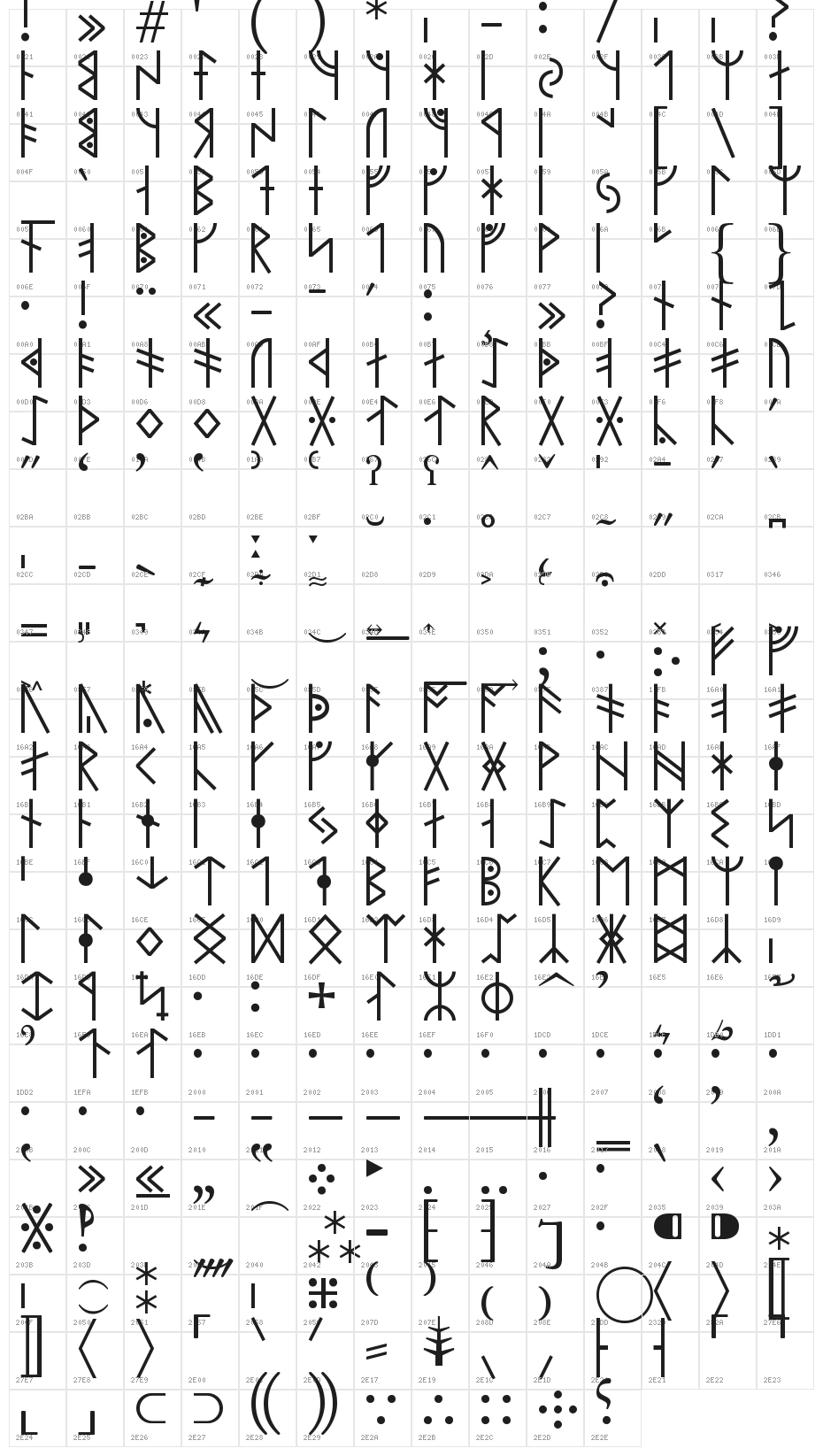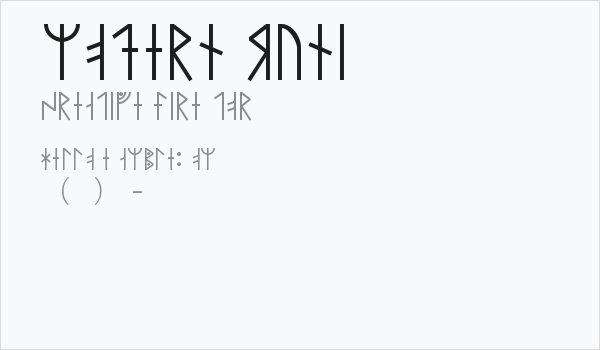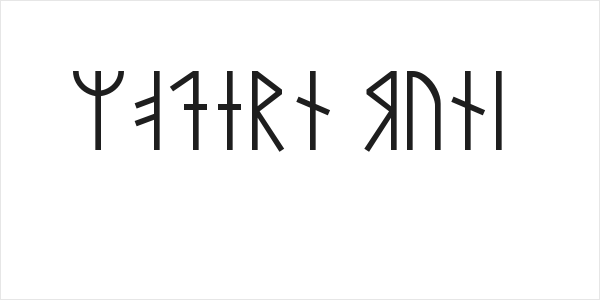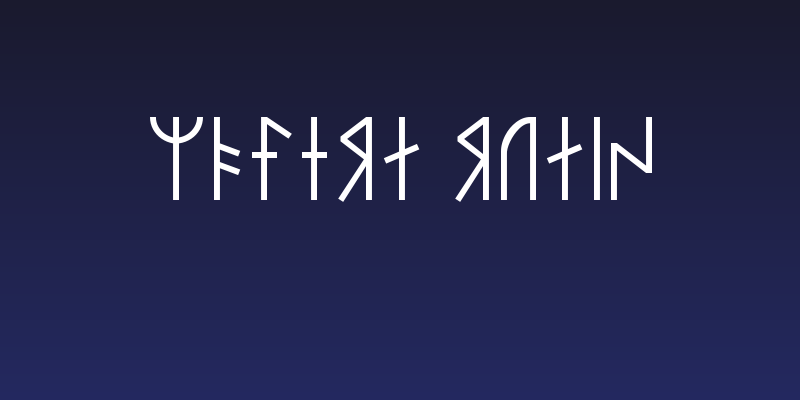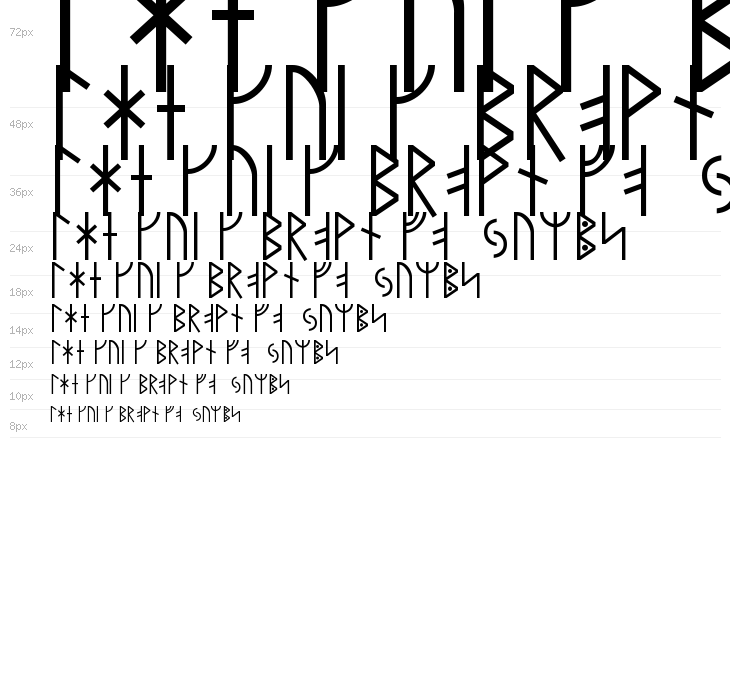
Modern Runic Font
| Caso d'uso | Logos, Headlines, Themed Events |
| Progetti proposti | Ideal for fantasy-themed designs, video game interfaces, book covers, and branding for products with a historical or mystical theme. |